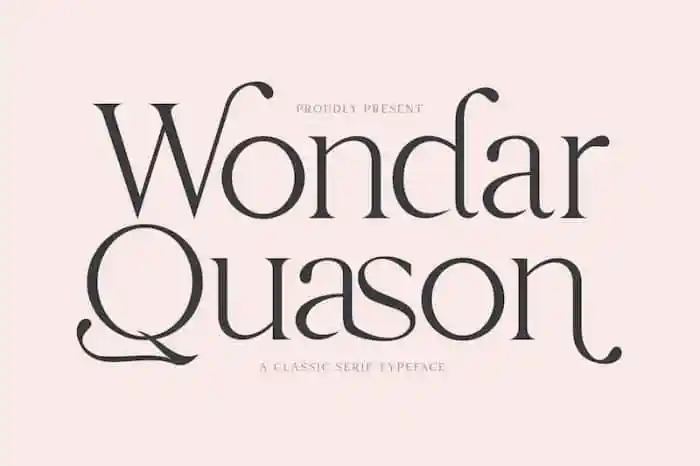
Wondar Quason Serif Font – Download Grátis
A Wondar Quason Serif Font é uma escolha perfeita para quem busca uma mistura de elegância moderna com a sofisticação vintage. Essa fonte serifa oferece ligaturas belas, diversos alternativos gráficos ornamentais e suporte multilíngue, tudo em um único pacote. Desenvolvida pela Maulana Creative em 99designs, essa criação moderna retrata a arte do tipo clássico dos anos 1800, trazendo uma toque sofisticado para os tempos atuais. Com seus alternativos inspirados no estilo Victoriano de hoje, Wondar Quason Serif Font oferece um nível de personalização incomparável. Sua característica mais destacada é a integração perfeita entre o moderno e o clássico, tornando-a ideal para qualquer projeto que busque um toque vintage em uma tipografia atual. Esteve atento às nuances do passado enquanto mantinha-se fiel aos padrões de qualidade modernos, criando uma fonte serifa que encanta tanto por sua elegância quanto pela sua capacidade de adaptar-se a uma ampla gama de usos.